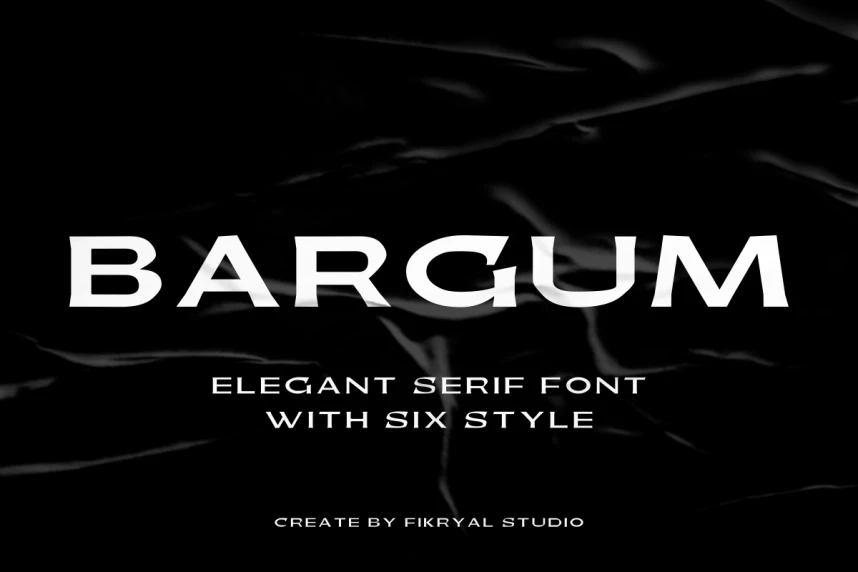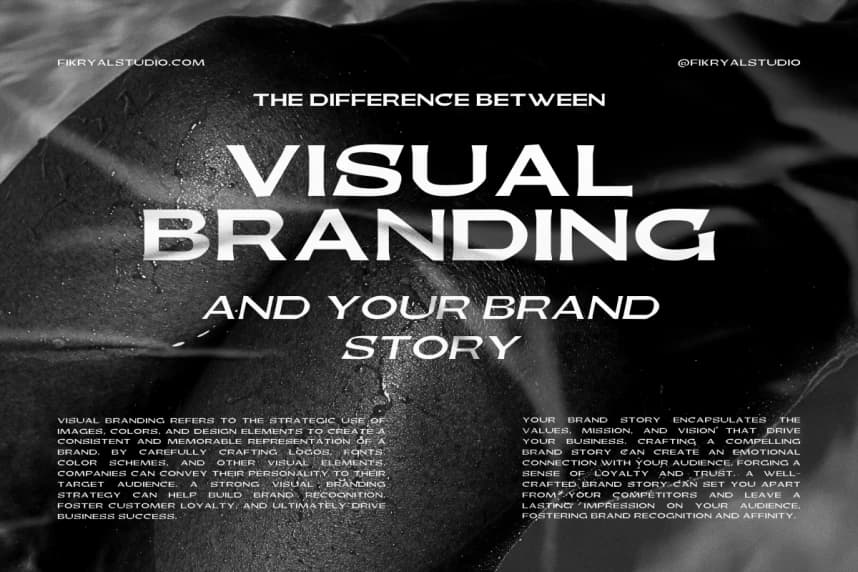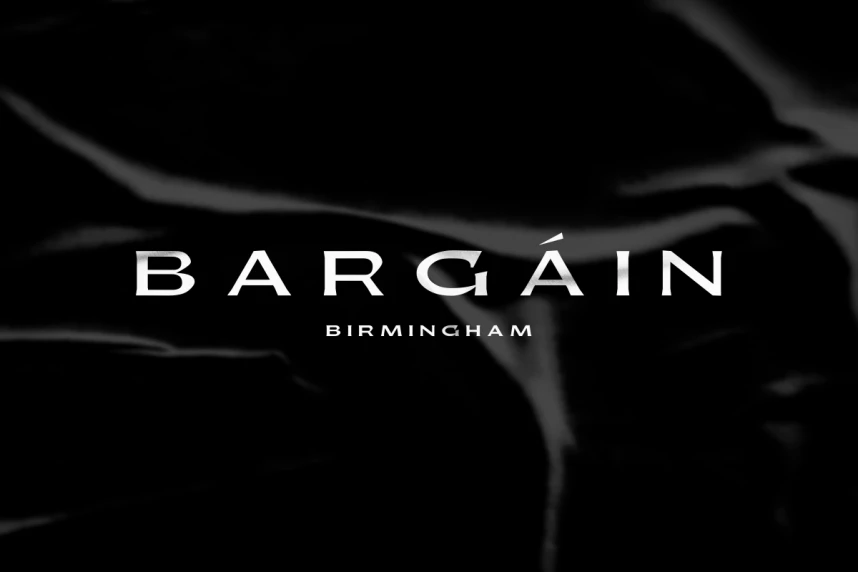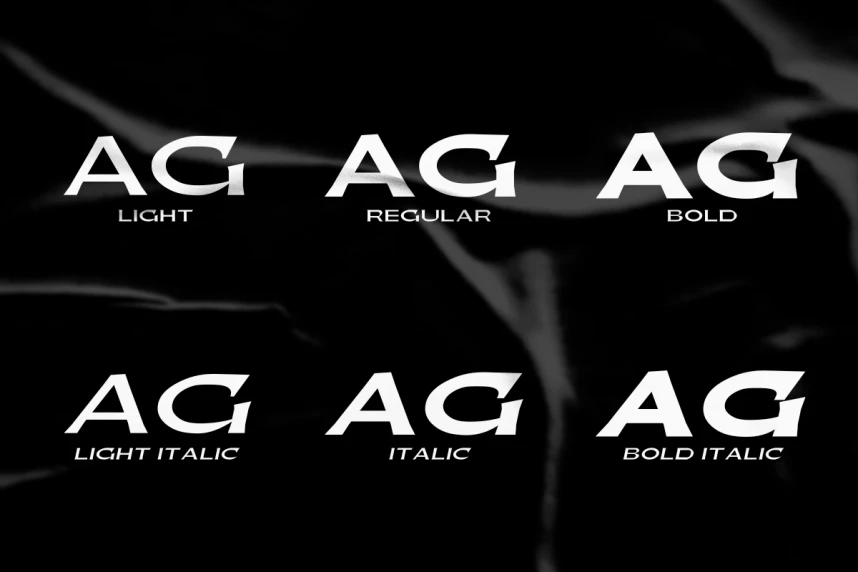
Bargum – Elegant Serif Font
Bargum - Elegant Serif Font, yaratıcı projelerinize zamansız bir zarafet katmak için tasarlanmış zarif ve gösterişli bir display serif font ailesidir. Light, Light Italic, Regular, Italic, Bold ve Bold Italic olmak üzere altı stile sahiptir; bu font ailesi, zarif ve profesyonel bir dokunuş talep ede
Bargum - Elegant Serif Font, zamansız bir zarafet katmak için tasarlanmış zarif bir display serif fontu ailesidir. Altı stile sahip olan—Light, Light Italic, Regular, Italic, Bold ve Bold Italic—bu font ailesi, zarif ve profesyonel bir dokunuş isteyen projeler için idealdir.